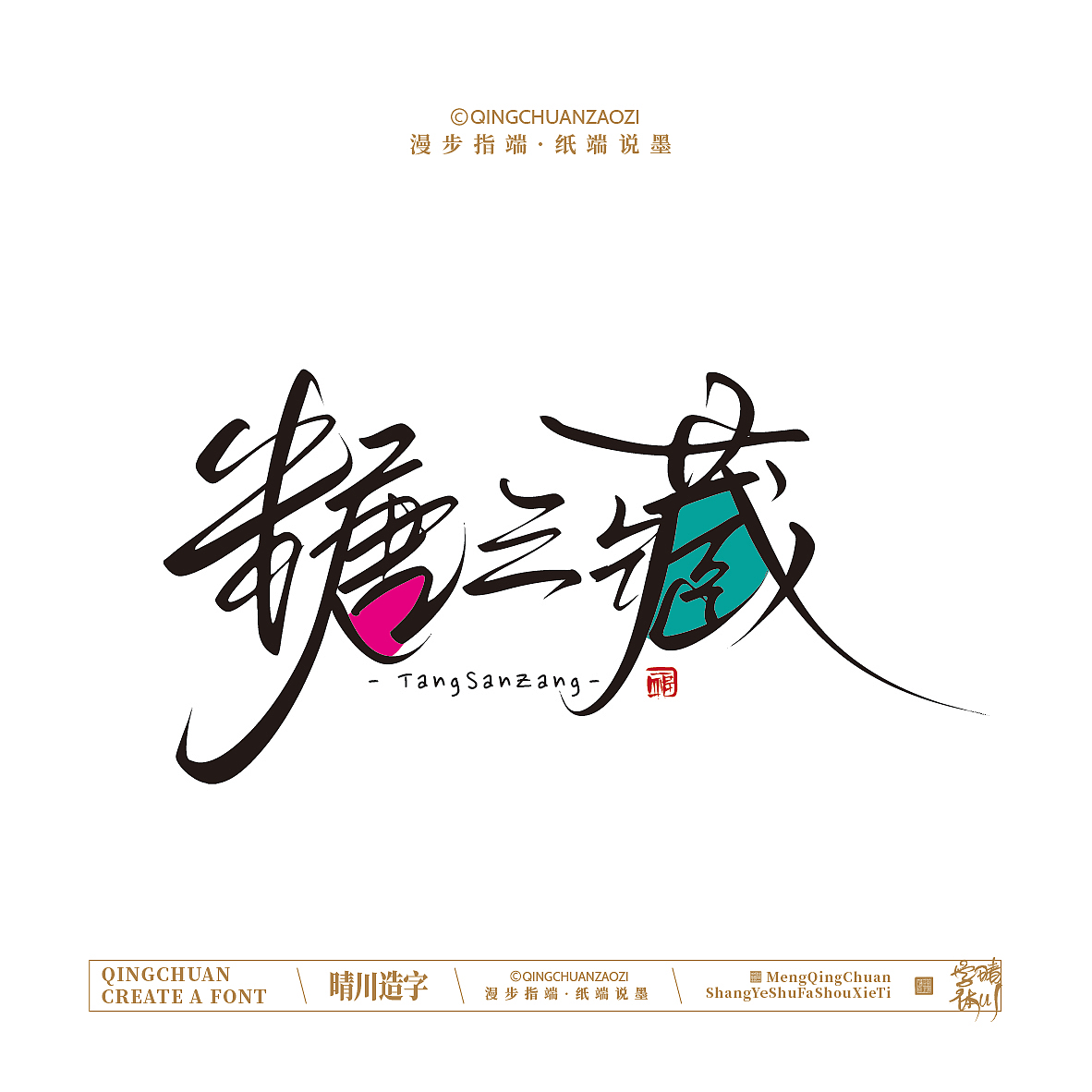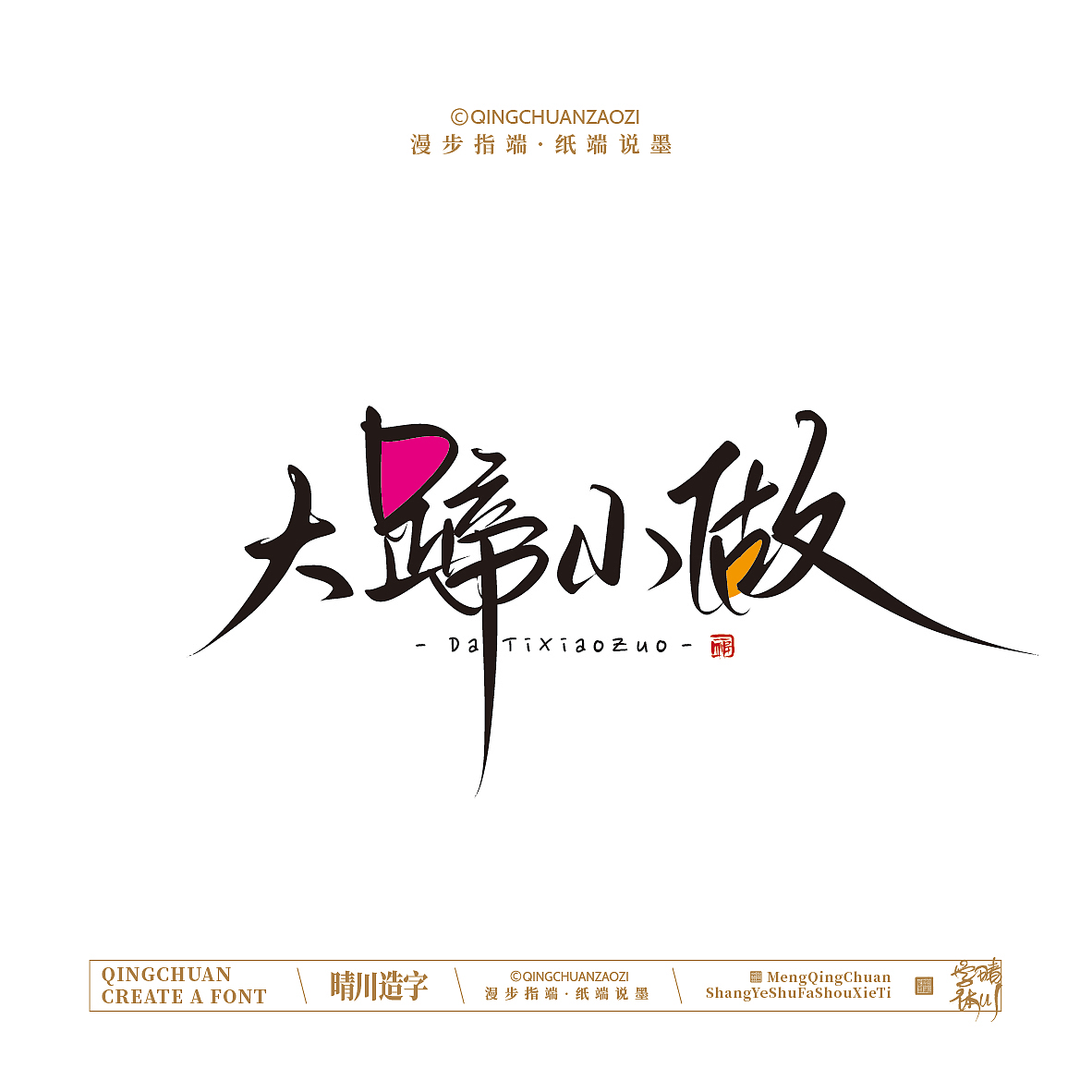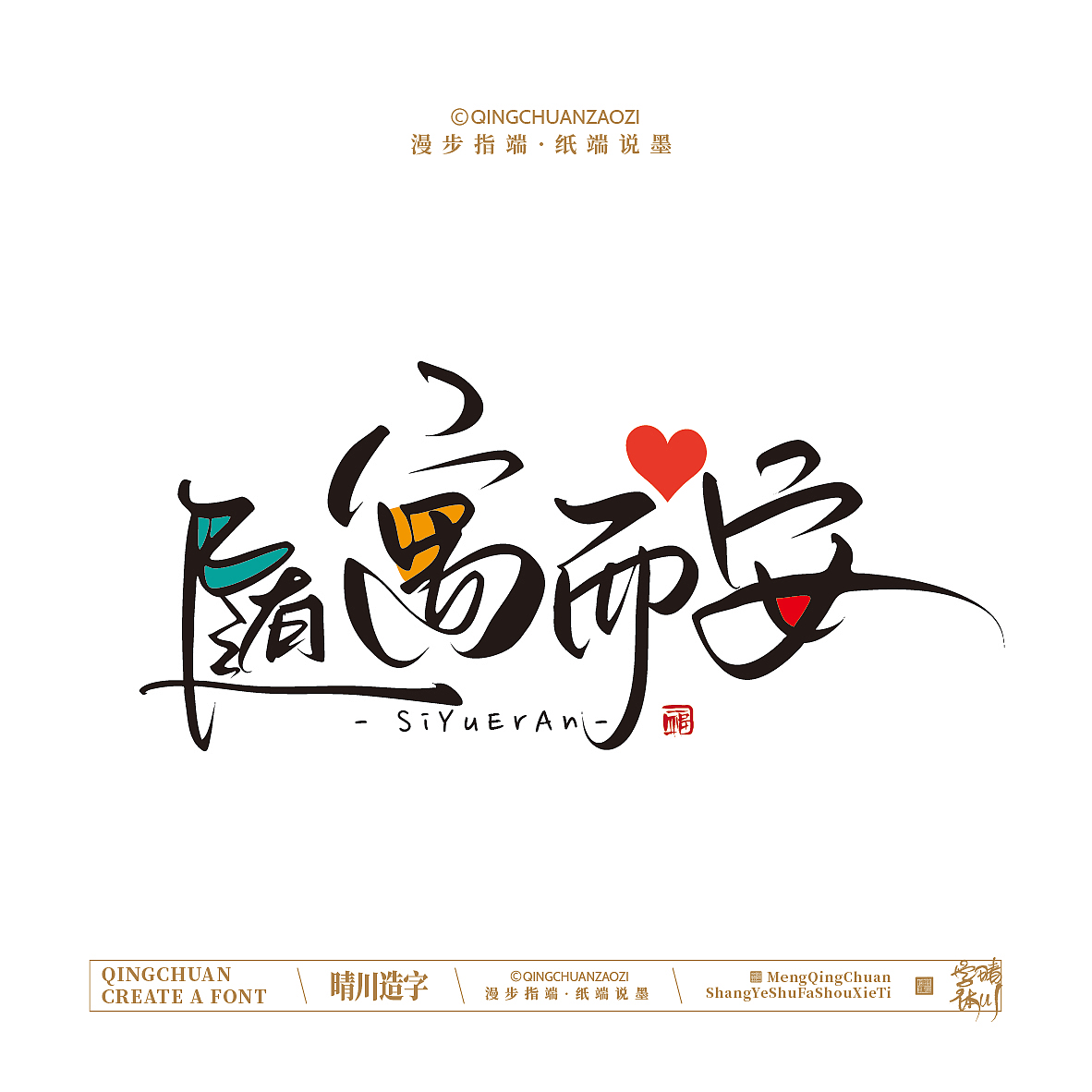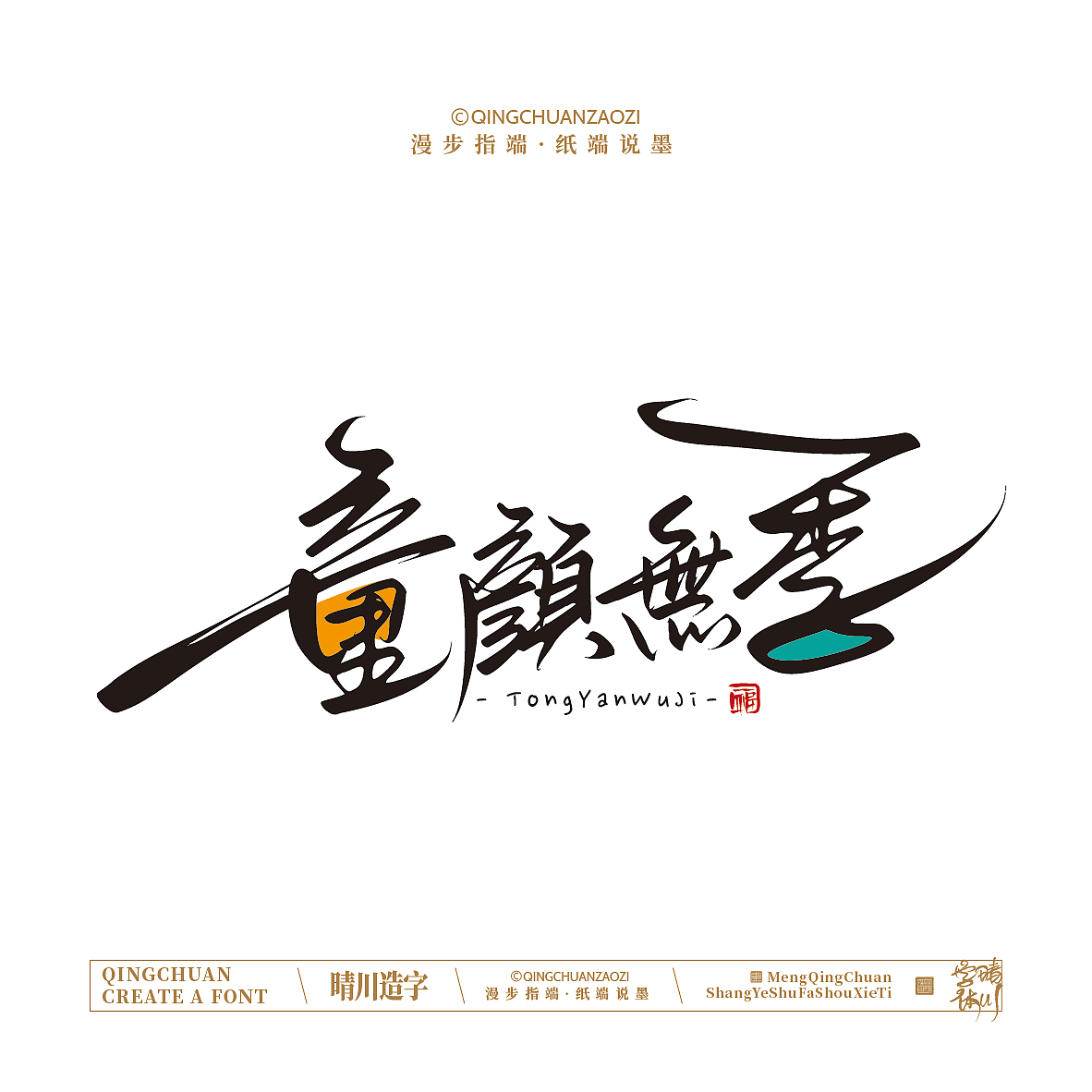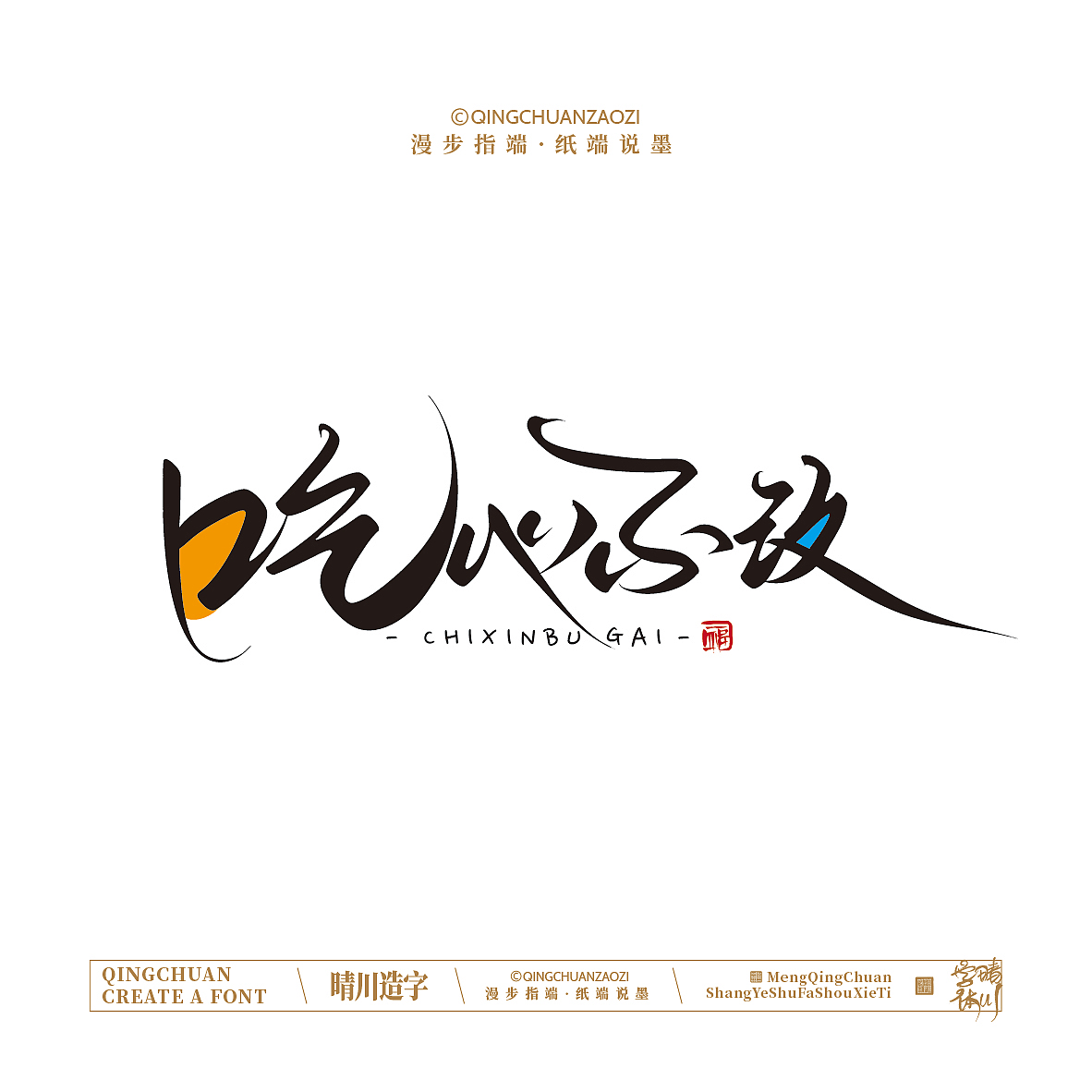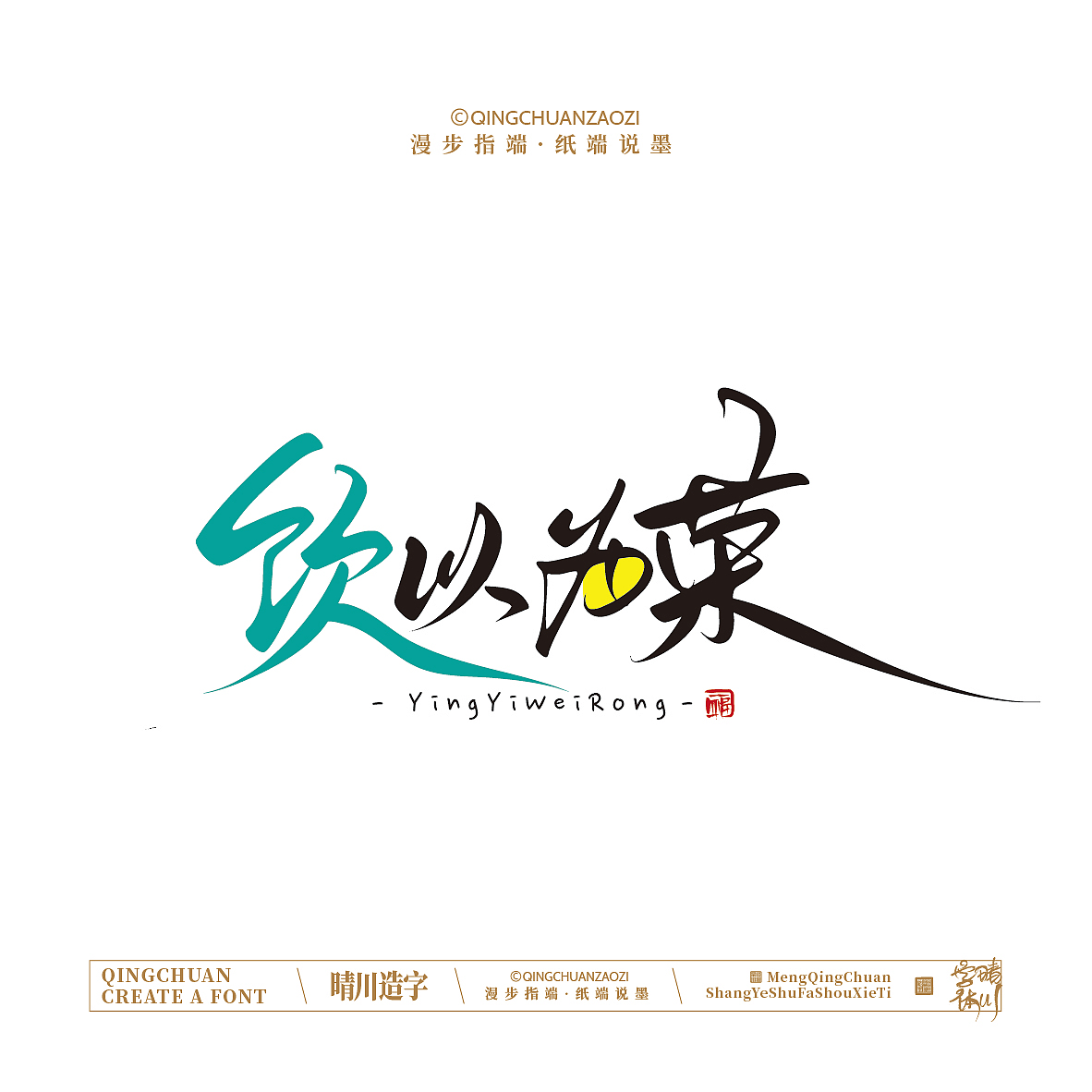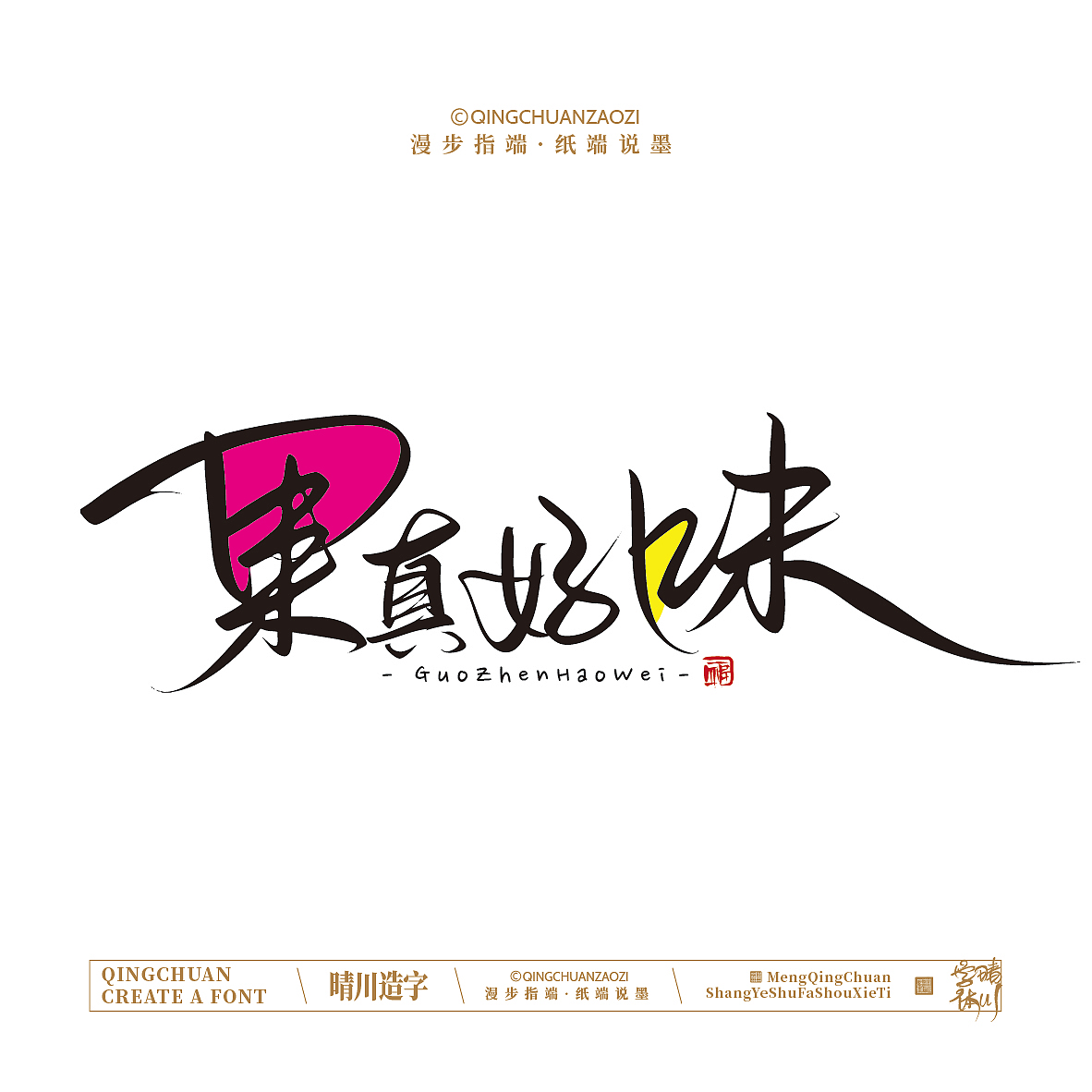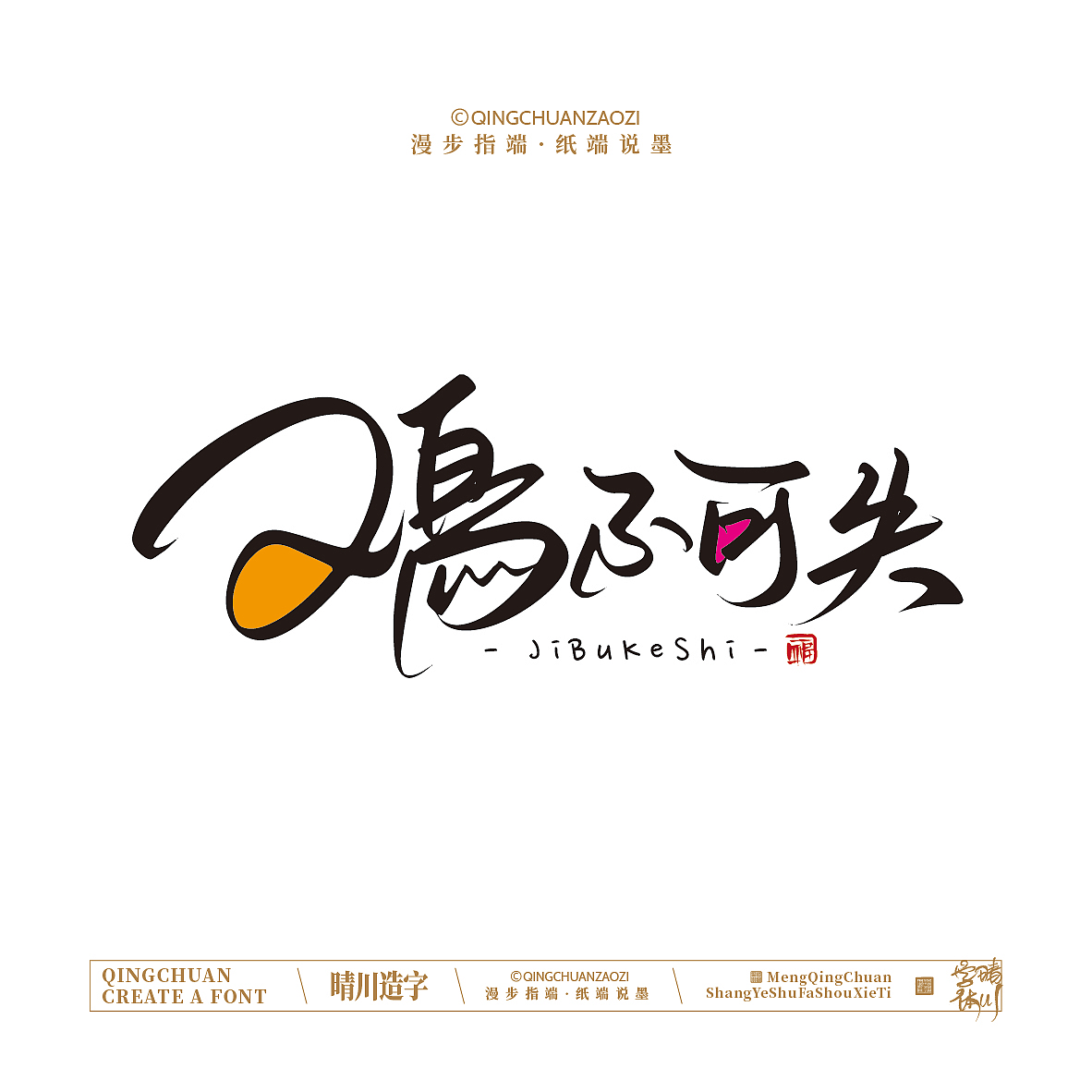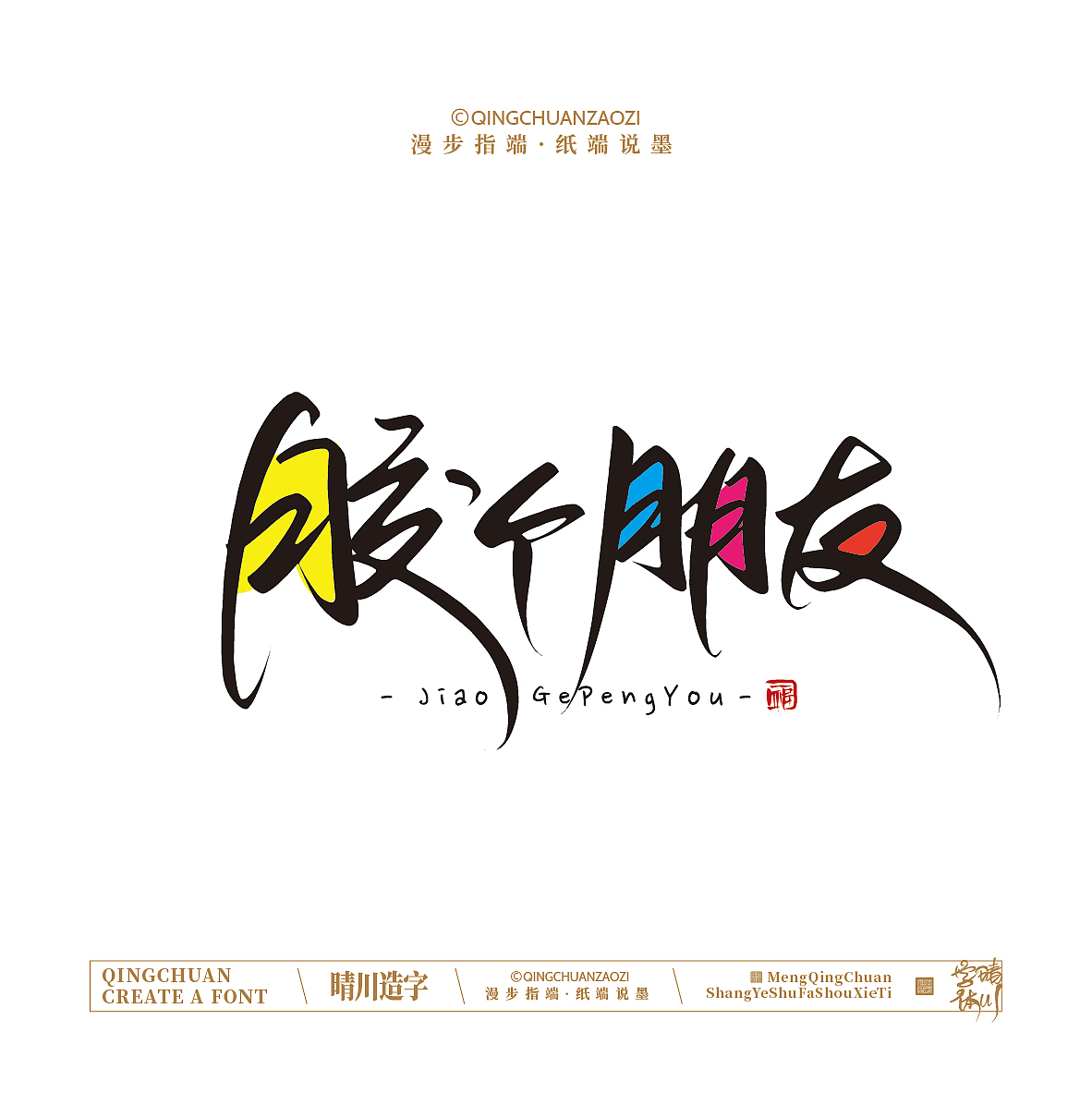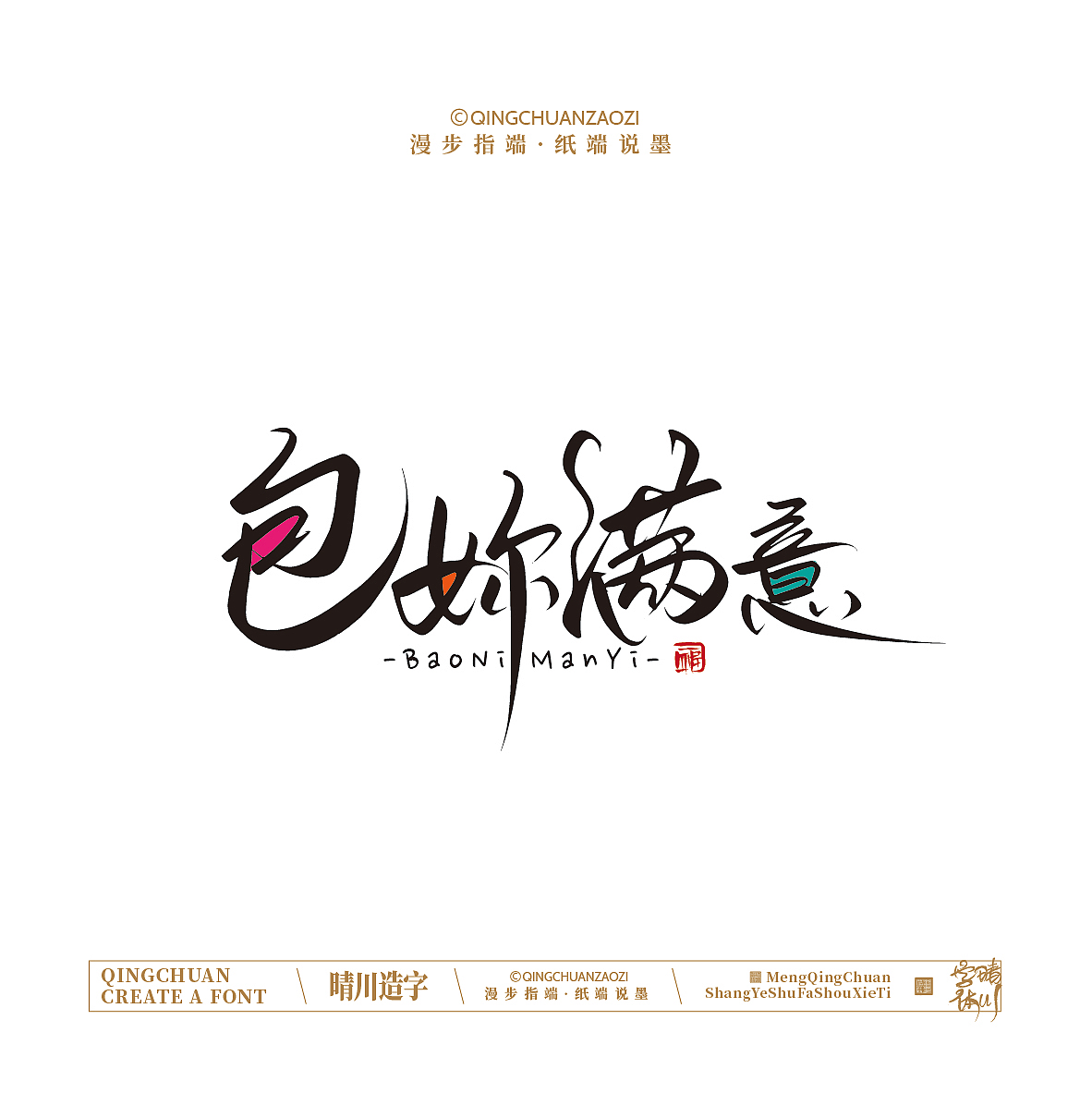
晴川手写|创意店名美术字(叁)
在“饿人谷”这个“吃心不改”的地方,每天都能看到“桃醉春风”“三锅鼎立”的场景,
“糖三藏”是“颜究所”的“主烤官”,主打“胶个朋友”,做的饭菜“煲你满意”,今天他将亲自下厨做他一直“饮以为荣”的菜系“大蹄小做”。
厨房里那真是“樱有尽有”各种佐料,只见他手拿把掐“锅色添香”火候掌握“喵不可言”,随着“食光煮语”真是“香约四季”,虽然我们是“读酥人”但是也禁不住这“柚惑食光”,闻一下都感觉“腊么好吃”,于是我们开启了“瓶空计划”
趁他不备“鸡不可失”我们迅速拿起“钙世无双”吃了起来,“果真好味”,吃了以后绝对让你“莓有烦恼”,糖三不愧是“屏步青云”的“柜族青年”!
(终篇)
中国字体博大精深/字体笔画流转间承东方气韵/字形取自传统书法藏锋于形
以字为桥/传递「方寸之间,自有天地」的古今共鸣